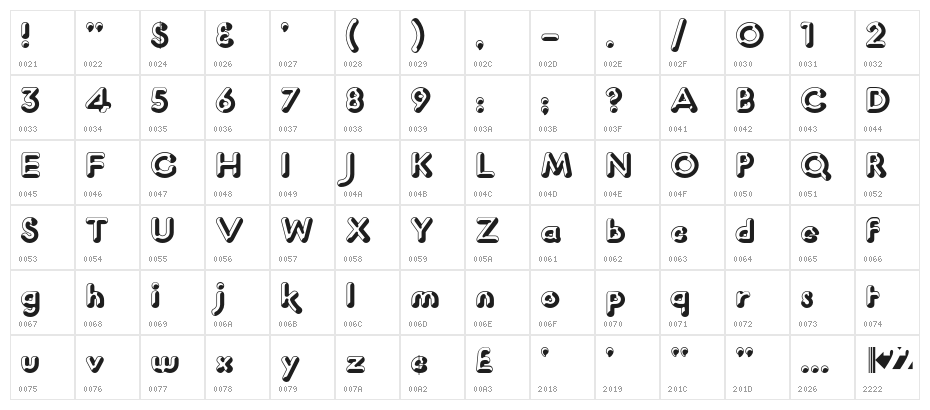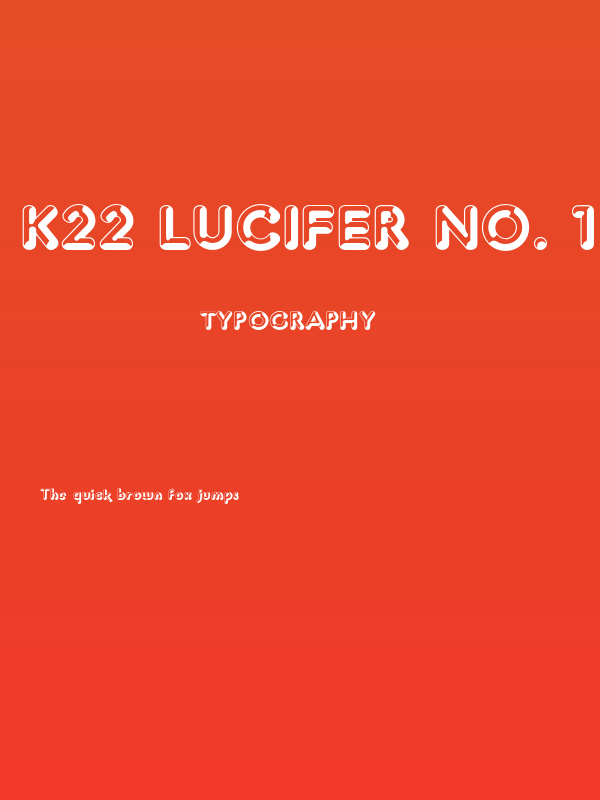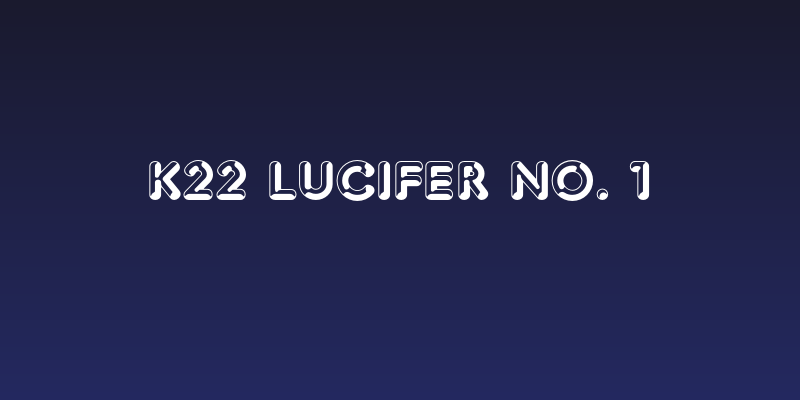
K22 Lucifer No. 1 Font
| Progetti proposti | Ideal for posters, children's books, video game graphics, and branding materials that require a fun and engaging look. |
K22 Lucifer No. 1